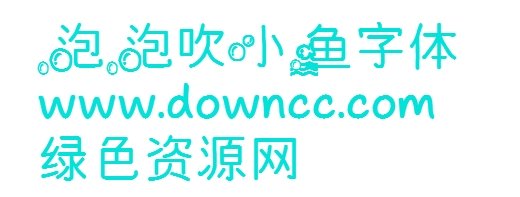
泡泡吹小魚字體是一款有著泡泡和Q萌魚兒形狀的卡通字體,讓你的文字間充滿了流動的小魚和圓圓的氣泡兒,給讀者帶來更多的視覺樂趣,快來綠色資源網(wǎng)試試吧!
泡泡吹小魚自帶泡泡和小魚兒形狀,免去設(shè)計上添加點綴的煩惱,讓設(shè)計師們使用更加方便,用于制作卡通文字、兒童畫報內(nèi)容也有著不錯的效果。
泡泡吹小魚字體,也稱作小魚吹泡泡字體,是一款十分活潑的pop字體,字庫完整,能滿足用戶的日常使用需求,給你的文字內(nèi)容不一樣的裝飾和美化,很有自己的特色風(fēng)情。